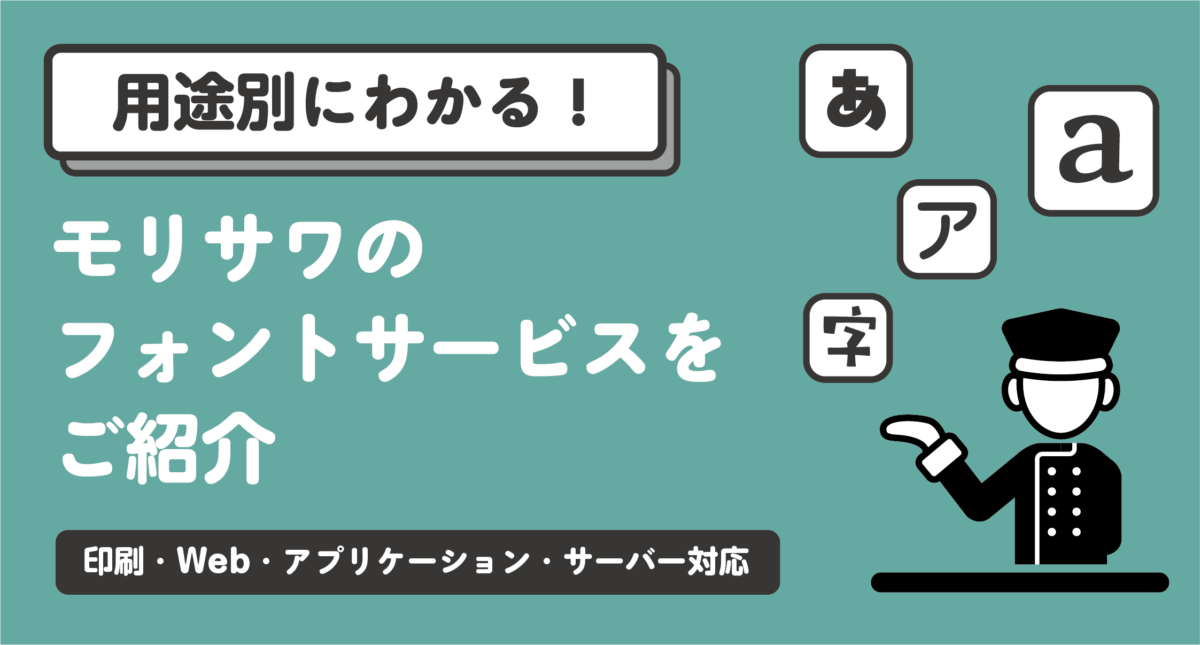
近年フォントサービスが多様化し、印刷物・Webサイト・Webアプリ、さらにはサーバーを介した自動組版まで、さまざまな用途に対応するものが登場しています。
そこで「気付かないうちにライセンスに違反していた」「使いたい場面で使えなかった」といった落とし穴にハマらないよう、本記事では4つの“やりたいこと”から逆引きして、目的に合ったフォントサービスをご紹介します。フォント製品の使い分けに迷っている方は、この機会にぜひご一読ください。
① 印刷物やグラフィック制作に使いたい方へ(書籍、ポスター、チラシなど)
商標登録も可能なフォントサービス「Morisawa Fonts スタンダードプラン/Select24/Select8」がおすすめ
チラシやポスター、会社案内や冊子など、印刷物の制作に取り組む方にとってフォント選びはとても重要なポイントです。文字の選び方ひとつで、読みやすさや印象が大きく変わり、伝わり方にも差が出てきます。
Morisawa Fontsは日本語書体はもちろん、多言語対応の書体も豊富に揃っているフォントサービスです。明朝体やゴシック体などのベーシックな書体から、UDフォントや個性的なデザイン書体まで幅広く網羅されています。制作物のトーンや用途に合わせて、最適なフォントを柔軟に選べる自由度の高さは、印刷・出版・デザインなど多くの現場で活用されています。
▼こんな方におすすめ
・グラフィックデザイナーやDTPオペレーターとして業務に携わっている方
・自治体や企業の広報担当で印刷物を内製している方
②Webでもフォントの個性を活かしたい方へ
多様なデザインバリエーションで高速配信も実現「Morisawa Fonts Webフォント/Liteプラン」がおすすめ
Webサイトでは多言語対応や視認性が求められるシーンが増えており、読みやすさや一貫性のある文字表現がUXに直結しています。「Webサイトにも紙と同じように、さまざまなフォントが使えたら……」と思ったことはありませんか?
インターネットを通じてフォントを配信し、Webブラウザで表示させるWebフォントサービスを活用すると、デザイン性の高いフォントも手軽にWeb上で使うことができます。
▼こんな方におすすめ
・Webの視認性や可読性を改善したい方
・検索性の向上や、自動翻訳・音声読み上げなどの機能と連携させたい方
③サーバー上のフォントを利用して、名刺/年賀状/請求書などデジタルな成果物を出力したい方へ(PDF生成など)
専用ライセンス:「Morisawa サーバーフォントライセンス」がおすすめ
Web上で年賀状や名刺発注、チラシなどのテキストを指示してPDF生成したいというケースもありますよね。「サーバー側での組版に活用するフォント」として専用のフォントサービスをご用意しています。
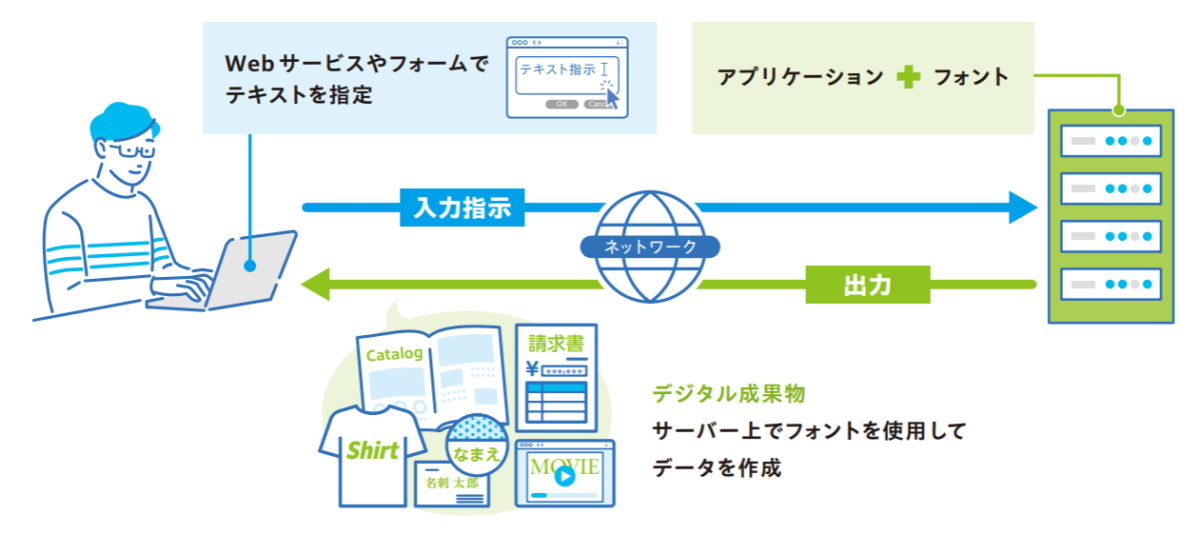
▼こんな方におすすめ
・組版サーバーシステムを使ってPDF出力したい方
・Web To Printシステムを構築したい方
④アプリケーションやハードウェア、ゲーム作品に組み込んで使いたい方へ
直接フォントデータを実装する「組込みフォント」がおすすめ
産業・医療・工業製品のHMI、ゲームや各種アプリケーションソフトに組み込んでお使いいただく際は、「組込みフォント」という契約方法があります。
多言語への対応はもちろん、個別の用途に合わせたフォントライセンスを各種ご用意しております。ご利用を検討されている機器やアプリケーションがある場合は、「簡易評価版フォントデータ」にて実際に組み込んでお試しいただけます!
▼こんな方におすすめ
・操作画面やアプリUIでの利用を前提に、可読性に優れたフォントを希望される方
・ローカライズ業務で、言語ごとにイメージを損なうことなくユーザー体験を提供したい方
・軽快に動作するように、フォントファイル容量を低減化したい方
制作・開発の初期段階では「フォント環境の整備」がとても大切です。フォントは 情報をわかりやすく伝える力とブランド体験を高める力を兼ね備えた、UIの根幹を支える重要な要素だからです。